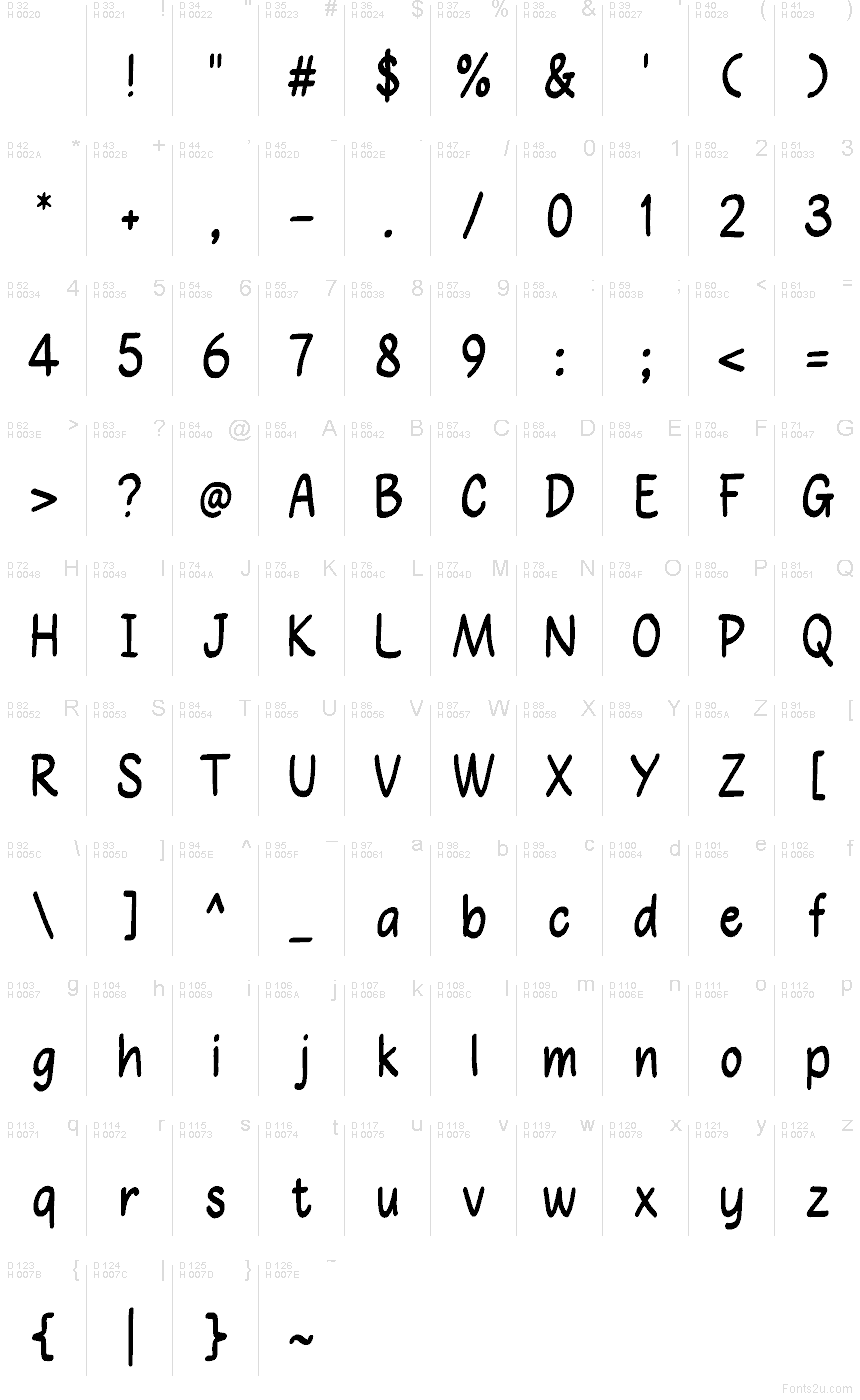
Panda Boss
Шрифт Panda Boss від Hello Good Studio — це безкоштовний рукописний шрифт з м’якими, невимушеними штрихами та округлими, відкритими формами, що нагадують швидкі записи маркером. Літери зберігають плавний ритм без зайвої жорсткості, що надає дизайну природного та особистого характеру.
Panda Boss чудово підходить для логотипів, меню кав’ярень, пакування продуктів, запрошень, графіки для соціальних мереж та оформлення коротких цитат, оскільки його дружня рукописна форма створює прямий і неформальний тон. Він також ідеально впишеться в етикетки та акценти на постерах, коли вам потрібен текст, який відчувається створеним вручну, а не за суворим шаблоном.